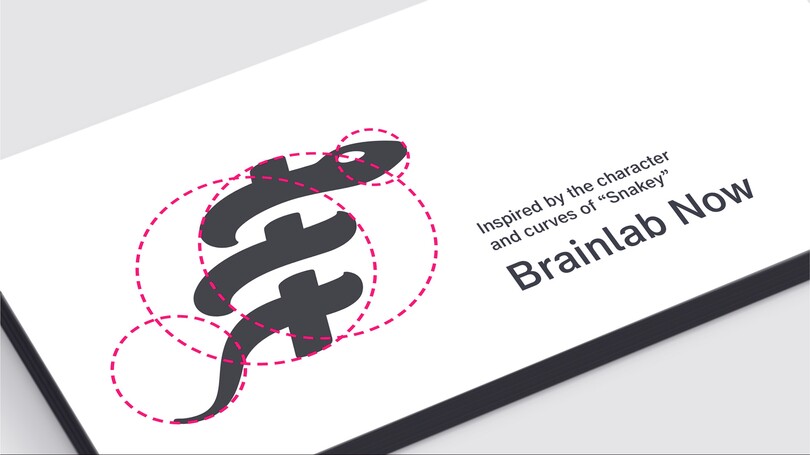
Maßgeschneiderte Helvetica Now für das Rebranding des Med-Tech-Unternehmens Brainlab.
„ Schon bei den ersten Gesprächen mit dem Brainlab-Team war klar, dass die Helvetica optimiert und nicht überarbeitet werden muss. „Helvetica Now Text war unser Ausgangspunkt. Im weiteren Verlauf mussten wir einen Satz neuer Condensed-Master und mehrere Versionen von Schlüsselzeichen entwerfen, um die beste Lesbarkeit in kleinen Größen zu garantieren. Diese Herangehensweise war ideal für Brainlab Now, da sie uns die Flexibilität gab, viele Iterationen von Proportionen, Öffnungen und Abständen zu testen, sodass wir das Design ständig auf die Bedürfnisse des Unternehmens abstimmen konnten. “
Tom Foley, Creative Type Director.
Als weltweit führendes Unternehmen in der Medizintechnik hat sich Brainlab in München zu einer führenden Kraft entwickelt, die das Gesundheitswesen in den Bereichen Onkologie, Chirurgie und Digitalisierung des Operationssaals in großem Umfang verändert. Nach 30 Jahren war Brainlab bereit für ein komplettes Rebranding und wandte sich an Monotype, um eine maßgeschneiderte Version der Helvetica Now als Markenschrift in Auftrag zu geben.
Wie kann eine modifizierte Schrift das Branding eines Med-Tech-Unternehmens und seine Mitarbeiter mehr Profil verleihen?
Nachdem Brainlab 30 Jahre lang Helvetica als Markenschrift eingesetzt hatte, suchte das Unternehmen nach einer zeitgemäßen Version, die sich sowohl für eine Digital-first-Strategie eignet als auch die Marken-DNA sowie den Human-first-Ansatz des Unternehmens in sich trägt. Brainlab wünschte sich eine persönliche Hausschrift, die die Individualität des Unternehmens, seiner Produkte und seiner Mitarbeiter widerspiegelt.
„ Bei Brainlab ging es schon immer um Menschen. Wir wussten, dass eine maßgeschneiderte Schrift dazu beitragen kann, die menschlichen und digitalen Aspekte unseres Geschäfts zu vereinen und widerzuspiegeln … so wie wir beide Welten mit unseren Produkten verknüpfen. “
Stefan Vilsmeier, CEO/Founder.
Als Monotype 2019 die erste Helvetica-Neugestaltung seit 35 Jahren ankündigte, wusste Brainlab, dass das Monotype Studio der perfekte Partner für die Entwicklung des richtigen Schriftdesigns sein würde. Eine eigene Version mit dem Namen Brainlab Now würde kurzfristig eine maßgeschneiderte Identität liefern, die Brainlab visuell differenziere, ohne den Zeit- und Kostenaufwand für eine komplette Neuentwicklung.
Als Kern einer umfassenden Rebrandings musste die neue Schrift Kriterien erfüllen wie:
• Bezug zur DNA der Marke
• digital first, also ein Kind dieser Zeit
• für alle Sprachen gerüstet
• Menschlichkeit und Technik repräsentieren
• das Wesen von Brainlabs Schlangenlogo aufgreifen
Die Modifikationen.
In enger Zusammenarbeit mit dem Brainlab-Team entwickelte das Monotype-Studio eine individuelle Helvetica-Interpretation, die modern und menschlich ist und dem Geist der Marke entspricht, wobei praktische Anforderungen wie Lesbarkeit, Skalierbarkeit und Sprachkompatibilität berücksichtigt wurden.
„Schon bei den ersten Gesprächen mit dem Brainlab-Team war klar, dass die Helvetica optimiert und nicht überarbeitet werden muss“, sagt Tom Foley, Creative Type Director. „Helvetica Now Text war unser Ausgangspunkt. Im weiteren Verlauf mussten wir einen Satz neuer Condensed-Master und mehrere Versionen von Schlüsselzeichen entwerfen, um die beste Lesbarkeit in kleinen Größen zu garantieren. Diese Herangehensweise war ideal für Brainlab Now, da sie uns die Flexibilität gab, viele Iterationen von Proportionen, Öffnungen und Abständen zu testen, sodass wir das Design ständig auf die Bedürfnisse des Unternehmens abstimmen konnten.“
Um eine flexible Schrift für alles zu bekommen, die überall funktioniert und in jeder Größe einzigartig und effizient ist, hat das Monotype Studio die Zeichenbreite um 92,5 % verringert. So passen auch längere Texte problemlos in digitale, responsive Layouts. Außerdem haben die Font-Ingenieure das Verhältnis von Höhe zu Strichstärke an die schmalere Form von Brainlab Now angepasst. Eine kursive Version stand ebenfalls auf Brainlabs Wunschliste.
Brainlab GIF
Inspiriert vom ikonischen Schlangenlogo aus dem Jahr 1989 studierten Brainlab und Monotype genau, wie die dem Logo-Design innewohnenden Formen in die Schrift einfließen könnten. Man öffnete ausgewählte Klein- und Großbuchstaben, Ziffern und Satzzeichen und rundete letztere sowie Akzente von diakritischen Zeichen so ab, dass sich die Kurven des Logos hier wiederfanden.
Brainlab Snakey
Eine Marke, eine Schrift für alle.
Brainlab Now funktioniert über alle Kontaktpunkte der Markenkommunikation, von großflächigen Ausstellungsinstallationen bis hin zu mobilen Apps. Das Monotype Studio sorgte dafür, dass Brainlab Now für alle Nutzer leicht zu bedienen ist, einschließlich differenzierender Zeichen, die an allen möglichen Berührungspunkten konsistent bleiben.
Brainlab Now spiegelt das wider, wofür seine Marke steht: ein offenes Ökosystem und eine offene Architektur, die ein durchdachtes, erneuertes Branding für „jeden und überall“ erlaubt.
„Wir haben eine klar definierte Haltung und Persönlichkeit, die wir auf unsere gesamte Kommunikation anwenden, damit wir schnell erkannt, gut verstanden und leicht erinnert werden“, sagt Tobias Schalkhausser, Executive Vice President Marketing & Digital. „Unser Schriftbild entspricht dem Zweck von Brainlab und schafft Vertrauen in alles, was wir tun und getan haben, in der Vergangenheit, Gegenwart und Zukunft.“